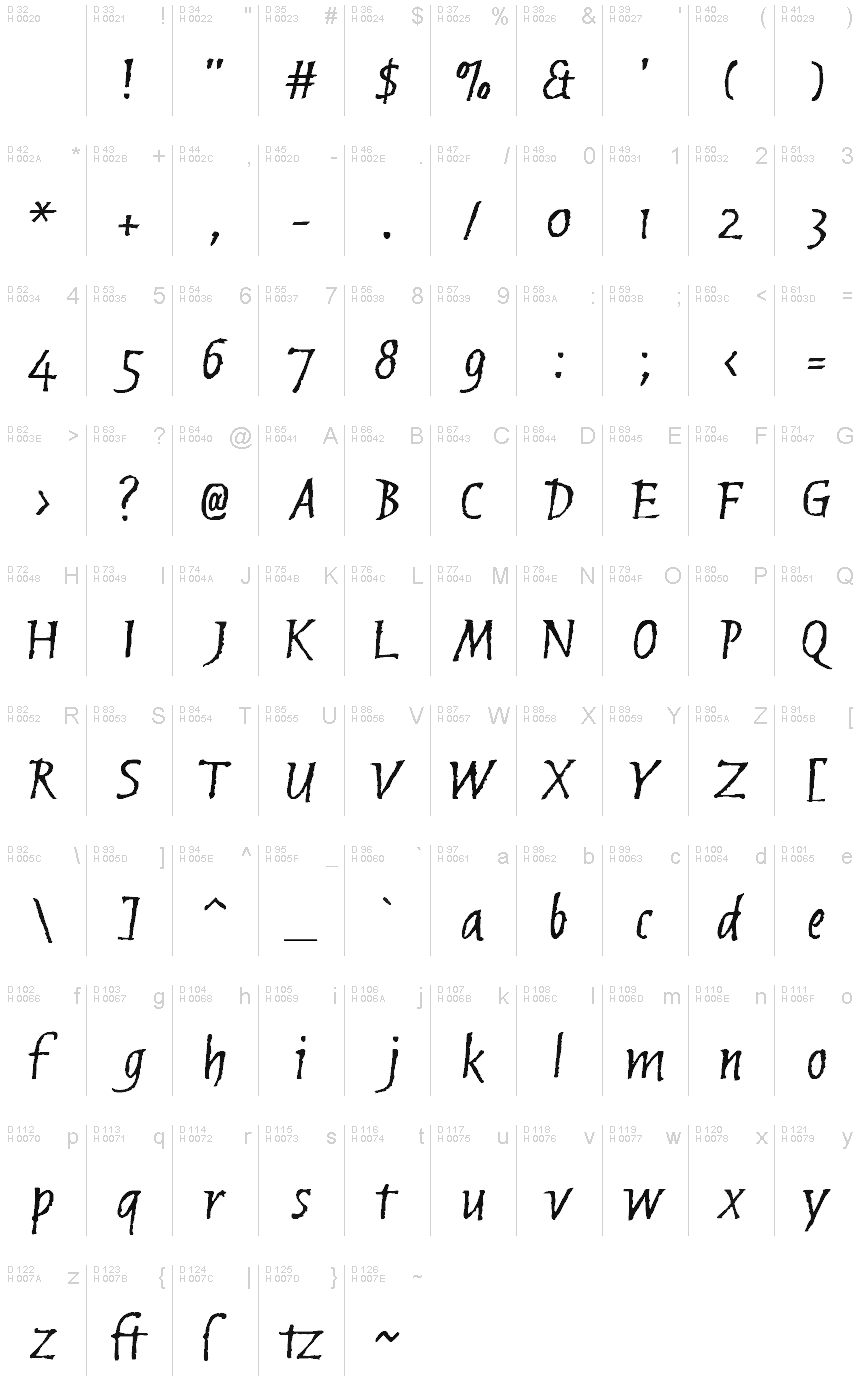
Brubeck AH von Fontgrube AH ist eine kostenlose, handschriftlich anmutende Schrift, die aussieht, als wäre sie schnell mit einem kratzigen, leicht trockenen Stift hingeworfen worden. Die Striche wackeln gerade so stark, dass sie menschlich wirken, und die schmalen, hohen Formen mit ihren tintigen Kanten verleihen jedem Wort einen lässigen, jazzigen Schwung. Sie ist informell, ohne kindisch zu wirken, und trägt eine Note böhmischer Raffinesse in sich, die in jedem klaren Layout hervorsticht.
Mit Brubeck AH erhalten Sie die Energie einer Handschrift, die wunderbar für Jazz- oder Indie-Konzertplakate, Albumcover, Menükarten, Lyrikbände, Theater-Flyer und kunstvolle Veranstaltungseinladungen funktioniert. Diese kostenlose Schrift glänzt vor allem in größeren Schriftgraden, wo ihre texturierten Kanten richtig atmen können. Kombinieren Sie sie mit einer einfachen, neutralen serifenlosen Schrift für den Fließtext, damit Brubeck AH bei den Schlagzeilen und Titeln glänzen kann.
Brubeck is a condensed, brush-like typeface, lively but neat, almost with a calligraphic touch. Forming connected word-pictures it is readable even in long lines. It comes with full Western European character set in the lower case, German Umlauts in uppercase, too. Brubeck contains a number of ligatures, some hidden in improper places of the font, please check with a character map program. There is also a long s on the bar character (see fontgrube blackletter mapping, even though Brubeck is not blackletter).